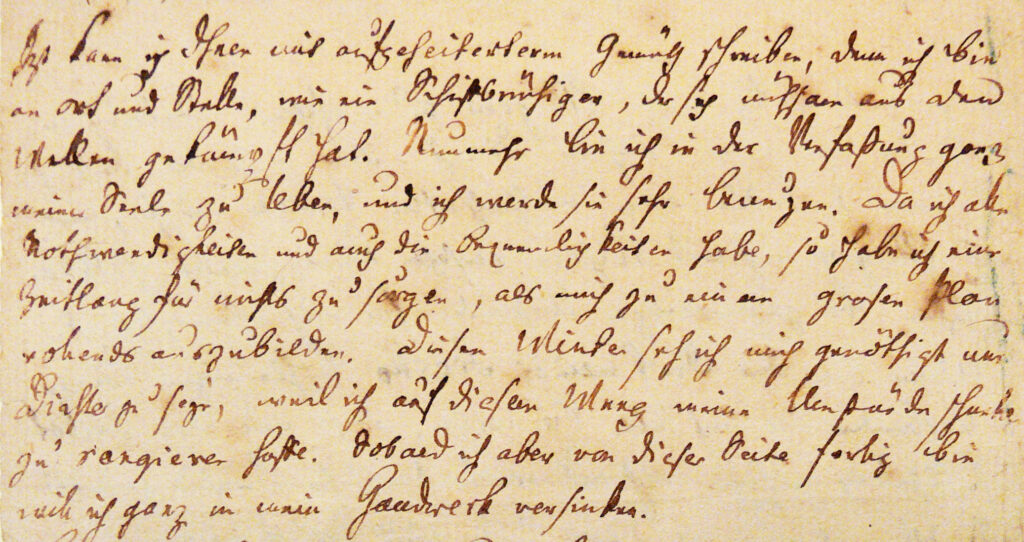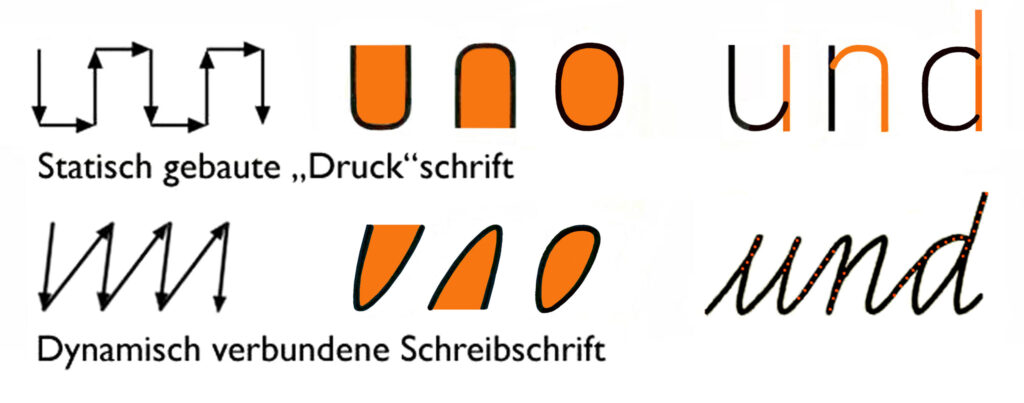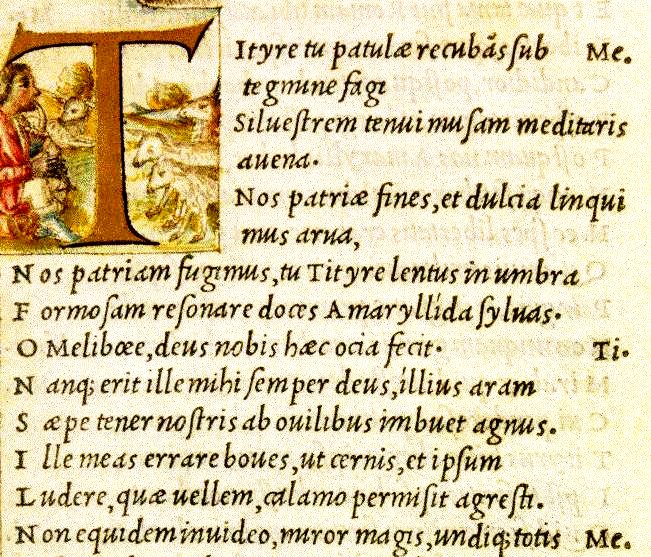
16.–18. Jh. die Kursive, Barock und Rokoko
1500 und die Kursive
Parallel zur Antiqua entwickelten sich um 1500 die kursiven Schriften deutlich weiter. Nach den ersten Ansätzen führte Aldus Manutius ihre Entwicklung und Verbreitung entscheidend voran. Grundlage war die Humanistische Kursive von Niccolò Niccoli, die in einem konstanten 45-Grad-Winkel geschrieben wurde. Manutius gestaltete daraus die erste kursive Drucktype, bestehend ausschließlich aus Kleinbuchstaben, während die Versalien aus einem geraden Schnitt übernommen wurden.
Von Ludovico degli Arrighi stammt die Cancellaresca, eine besonders feine Kursive. Beide Schriften wurden zur Basis aller folgenden lateinischen Handschriften und verbreiteten sich in ganz Europa. Während Kursiven heute als Schriftschnitt innerhalb der Antiqua gelten, standen sie im 16. Jahrhundert noch als gleichberechtigte Schrift neben ihr. Erst im 17. Jahrhundert begann man, gerade Schnitte systematisch mit passenden Kursiven zu kombinieren.
Der Begriff „kursiv“ (von lat. currere = „laufen“) bezeichnete ursprünglich nicht die Schrägstellung, sondern die fließende Verbindung der Buchstaben.
1700 – Barock und Rokoko
Um 1700 veränderten feinere Drucktechniken und die barocke Stilrichtung das Schriftbild. Typisch waren schwungvolle Linienführungen, die im Rokoko in dekorativen Spielereien gipfelten. So entstanden elegante Schreib- und Kursivschriften.
Zwischen 1700 und 1800 galt Holland als Zentrum der Typografie, wo Schriften wie die Janson Text und die Fleischmann entwickelt wurden. In England schuf John Baskerville mit seiner Baskerville eine elegante Barock-Antiqua, während William Caslon 1722 mit der Caslon Old Face eine der langlebigsten und einflussreichsten Antiqua-Schriften entwarf.